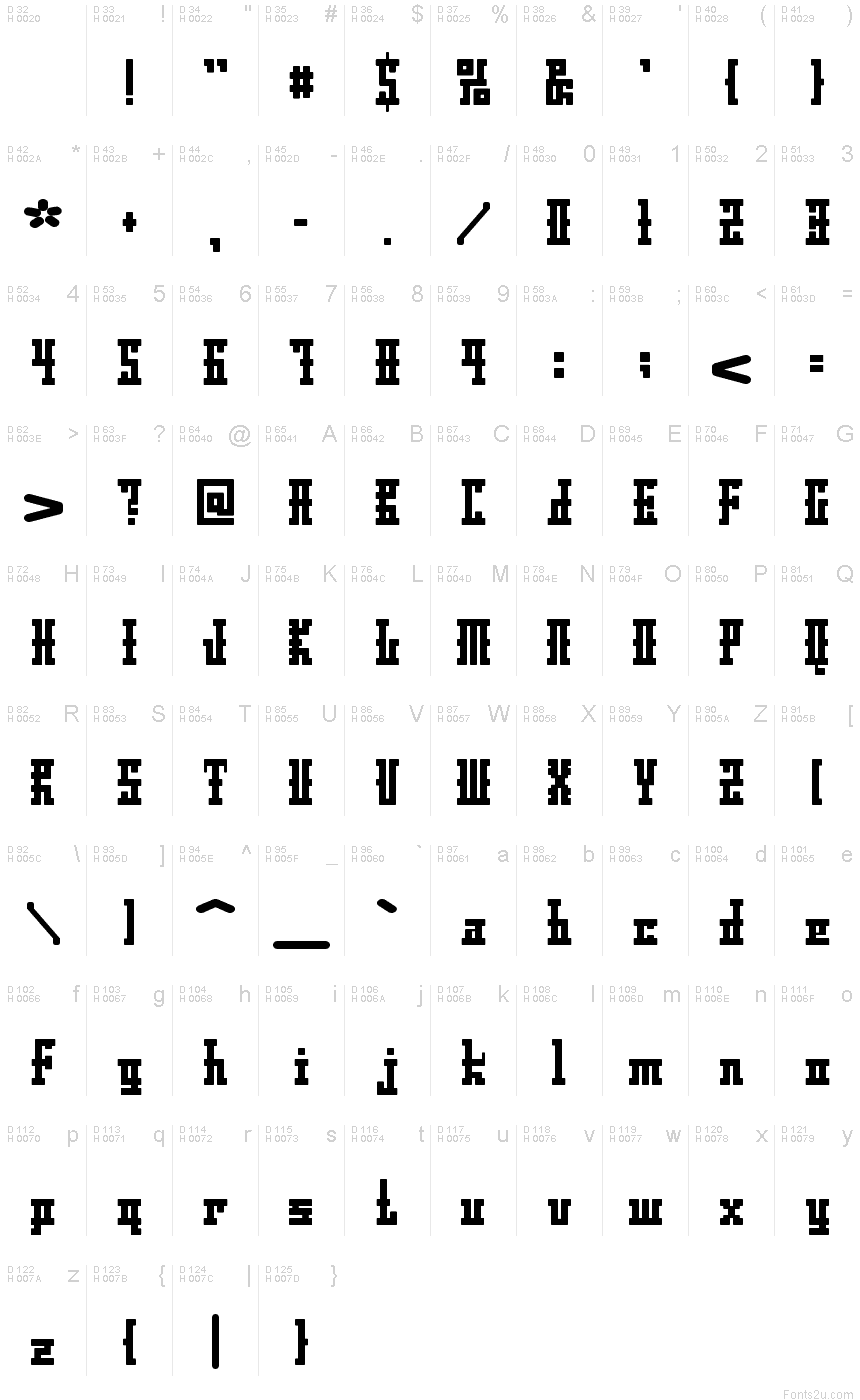
خط DS Ayaks من تصميم Dubina Nikolay هو خط عرض مجاني من فئة السلاب سيريف (Slab Serif) ذو طابع كتلوي وبنية ميكانيكية صارمة. تلتحم فيه تذييلات عريضة مستطيلة بالقوائم الرأسية، وتتشكل الحروف من خطوط أفقية ورأسية حادة، بينما تنعدم المنحنيات فيه تقريبًا.
تُعد اللوحات الإرشادية واللافتات المجال الأمثل لاستخدامه، حيث تشبه هيئته الصارمة الألواح المعدنية المقطوعة أو العلامات الصناعية. كما تناسب بنيته الصارمة ملصقات الحفلات الموسيقية، ورسومات الألعاب، والمنتجات الدعائية المتمحورة حول الآلات، والمصانع، أو طابع العمارة القاسية (البروتاليزم). وفي هذه السياقات، يمكن للنصوص أن تندمج ضمن التكوين البصري لتبدو مثل عوارض أو دعامات أو أجزاء من شعار هندسي.
Typeface it is created on motives of font Xolto (by Ray Larabie )